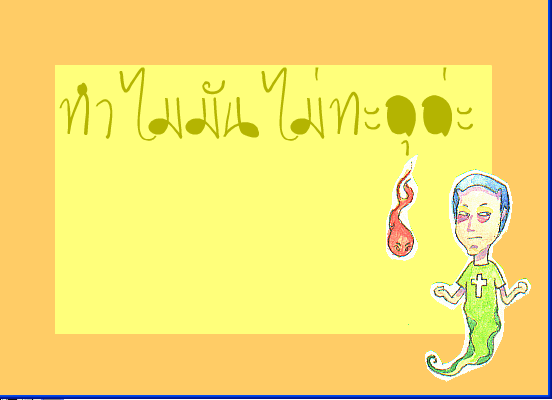
font ตัวแรกลองทำมาให้ดู
เอ้า นี่ผลการทดสอบ
ลองดู ง งูกะ ว แหวนครับ
สองตัวนี้นักเลงน่าดูเลย แต่ถ้าตั้งใจก็ไม่เป็นไรครับ
จงใจครับ จงใจ
ลายมือมันเป็นแบบนี้ จริงๆแล้วร เรือ ก็เป็นด้วย
แต่กดให้เล็กแล้วครับ
แต่เด๊ยวลองแต่งให้อีกรอบ
อันนี้เป็น logo ครับ
ตัวใหม่แก้
ว แหวน
กะ ง งู แล้ว
โลโก้ด้านบนครับ
ขอ revise font เป็นอันนี้
สุดท้ายแล้วจริงๆ
ผมเอาไปแก้สระ อุ และ สระอูแบบต่ำ สำหรับคำว่า กฎุมภี ครับ
เอ่อ ผมโดนหักจิตพิสัยเนี่องจากอะไรครับ  :44:
1. ถามมากไป
2. คุยผ่าน จมล มากไป
3. ไม่ได้คุ้ยกระจู๋ก่อนถาม
มันติดใจน่ะ
อยากรู้ว่าทำไมโดนหัก อ่านที่นี่ครับ
และโพสต์ข้างบนก็ทำให้ผมหักคุณตั้มอีกสอง :26:
เอ้อ คำว่า ฟ้อนต์ แก้เป็น ฟอนต์ (หรือ ฟ๐นต์) ก็ดีครับ จะได้เป็นศัพท์สากล
อืม มันส์ดีแฮะบอร์ดนี้
เข้าใจคิด
ผมว่าผมเข้าไปอ่านหมดแล้วนะครับหน้านั่น
แต่สงสัยจะอ่านไม่ละเอียด ด้านล่างๆ ยังไม่ได้อ่าน
ผมจะพยายามไม่ซีเรียสกะเรื่องข้างบนละกัน
เพราะมันจะส่งผลกะงานของผม (ไกล้จะส่งแล้วด้วย)
แต่ก็จะระวังตัวมากขึ้น
คุณแอน ตอนนี้ผมมีปัญหาอีกแล้วครับสำหรับ flash ที่ให้ลองทำ
ผมไม่ได save งานมานะ แต่ลองทำใหม่ได้ดังรูปครับ
คือเวลาพิมพ์แล้วตัวอักษรที่มันไม่เป็นเส้นเปิดมันจะตันแบบนี้ครับ
แอนช่วยดูหน่อย
ไม่ติดขอโทษ
เครียดเลยนะเนี่ย  :05:
เนี่ยอะครับ